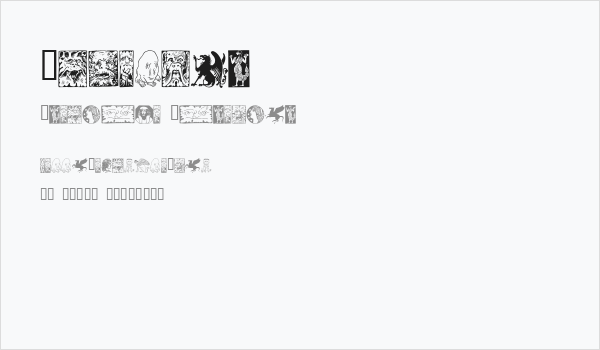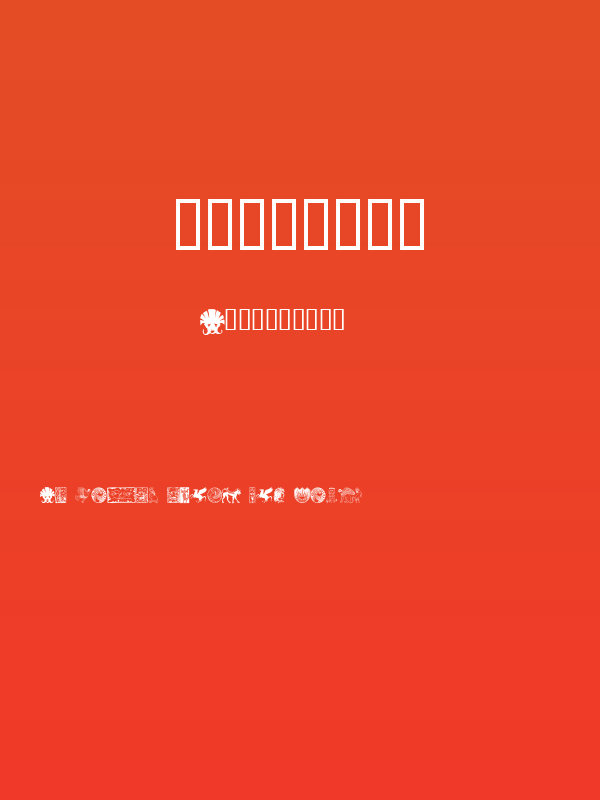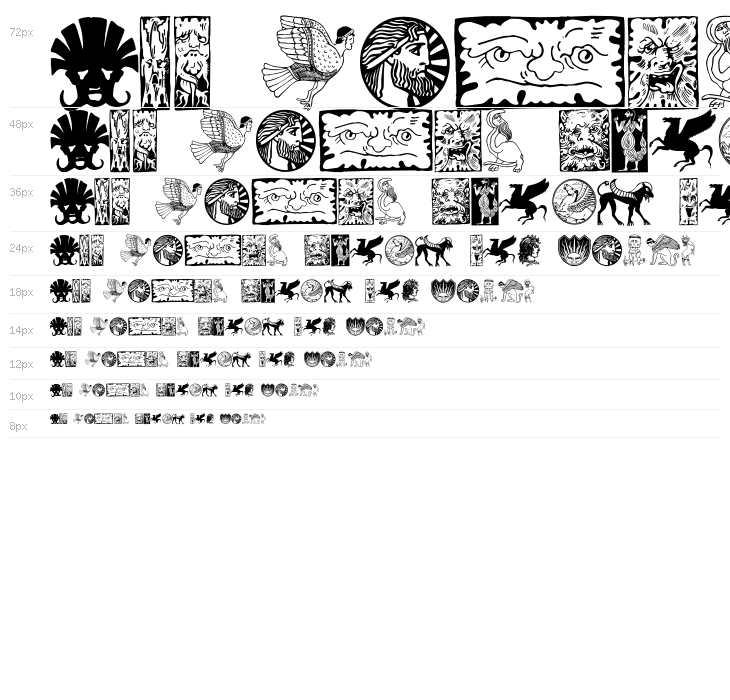
Fabeldyr Font
✎ Dingbats
| Gesamtstil | Decorative, Fantasy, Ornate |
| Anwendungsfall | Decorative elements, Themed graphics, Borders, Illustrative accents |
| Vorgeschlagene Projekte | Book covers, fantasy game titles, decorative borders, themed invitations, posters, and creative branding for fantasy or folklore-related projects. |